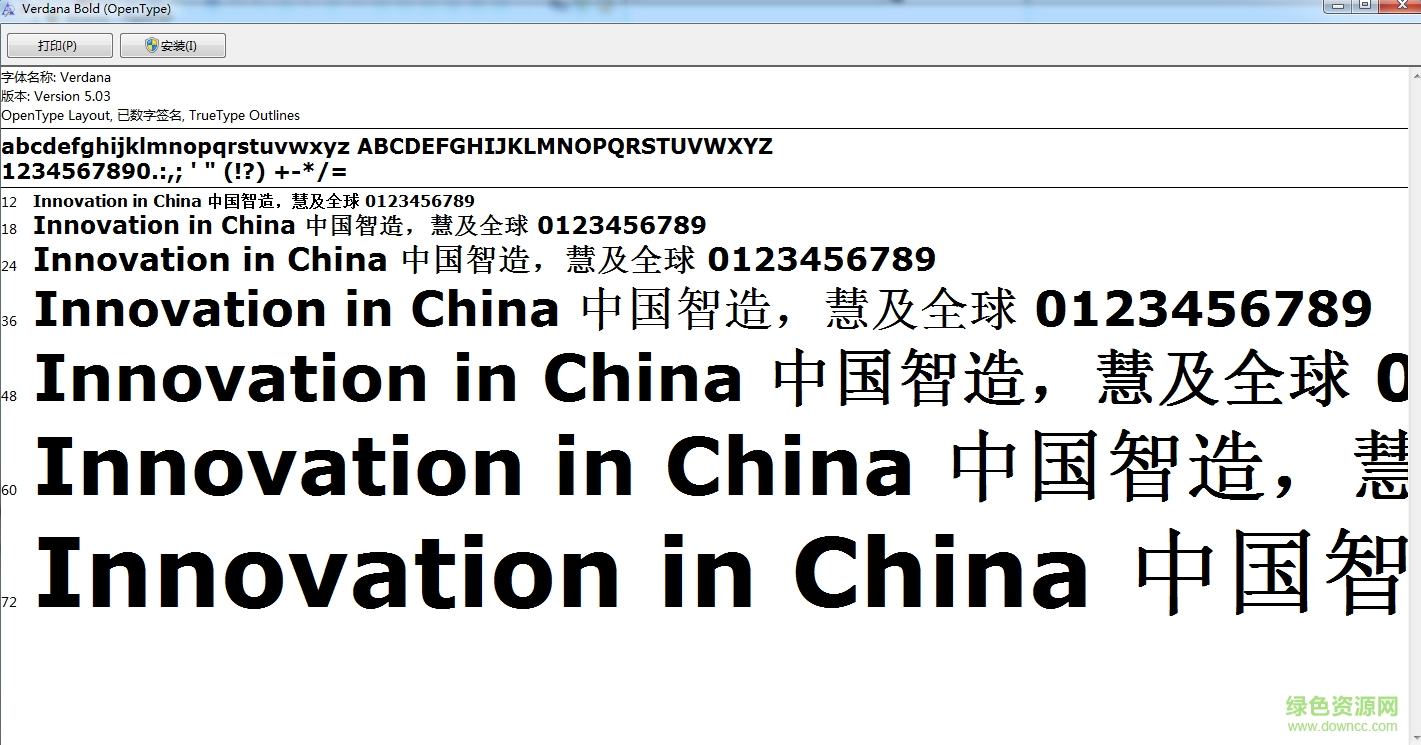
verdana bold字體是一款無(wú)襯線英文字體,該字體筆畫(huà)平直、粗細(xì)一致,莊重大方,印刷效果十分好,大家可在綠色資源網(wǎng)免費(fèi)下載!
無(wú)襯線體是隨著印刷工業(yè)的發(fā)展而來(lái)的,可以分為粗黑體(Grotesque)、過(guò)渡體(Neo-Grotesque)、古典體(Humanist)和幾何體(Geometric)四大類。